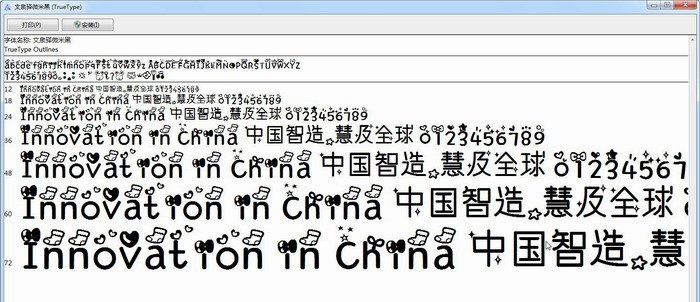
卡通愛情字體是一款專門為用戶用于蝴蝶結(jié)設(shè)計(jì)的字體,讓你快速設(shè)計(jì)圖案等必備字體,有需要的用戶歡迎下載!
以黑體為原型,在字體間嵌入大量的卡通圖案,標(biāo)點(diǎn)也換成了卡通圖案
即具有黑體的端正易認(rèn)風(fēng)格,又很有趣味性
以獨(dú)特的手寫風(fēng)格和俏皮的樣式,使字體看起來更加的個(gè)性時(shí)尚。